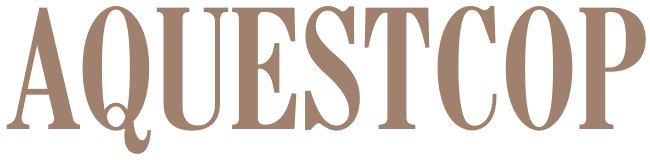
Welche Schrift könnte das sein?
Ich wäre dankbar für Eure Hilfe … die Schrift hat starke Ähnlichkeit mit der Benton Modern Display oder der Escrow Comp, aber so ganz stimmen die Details nicht.